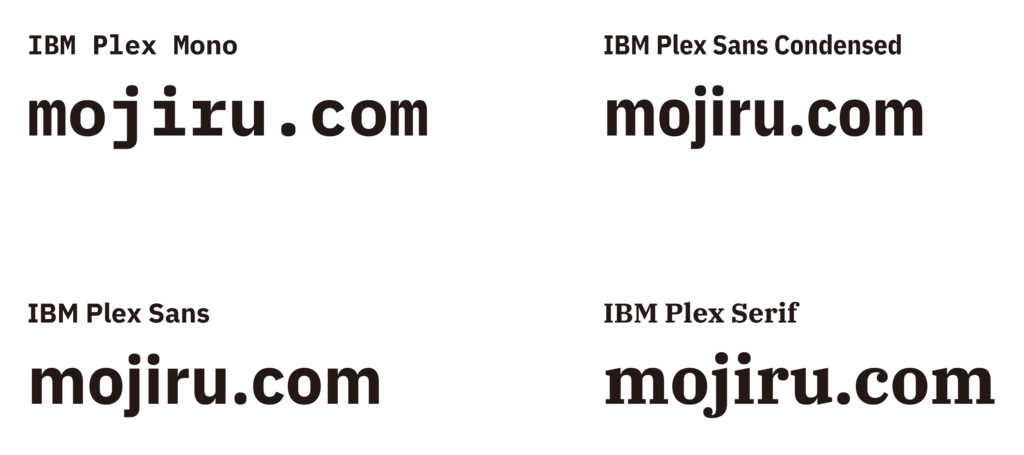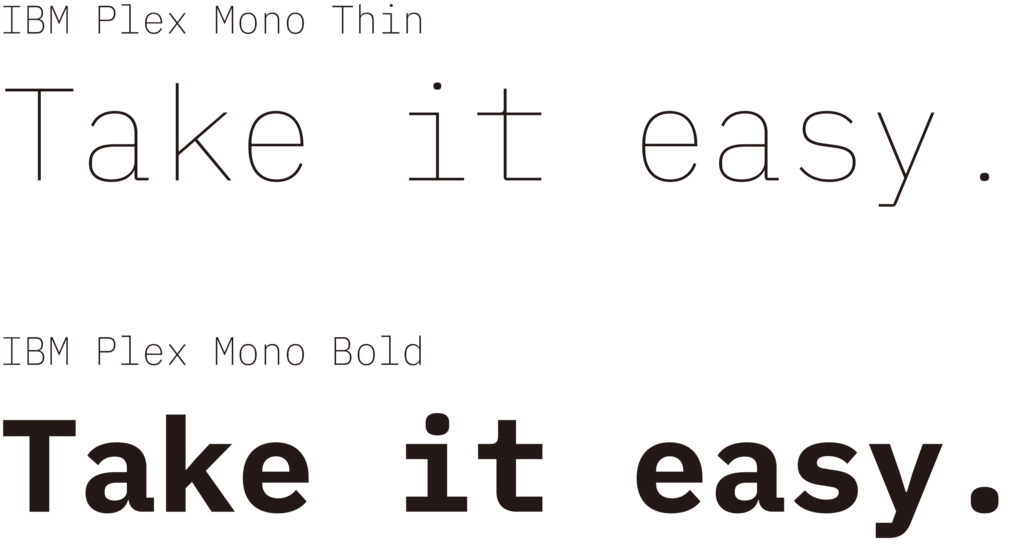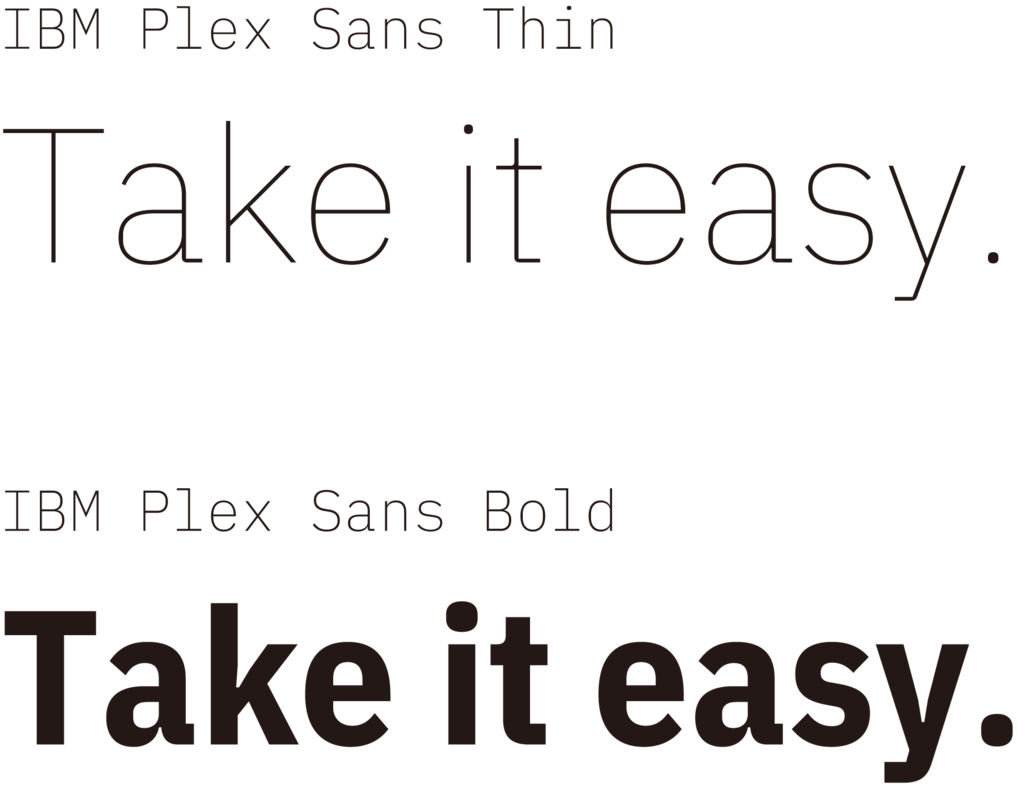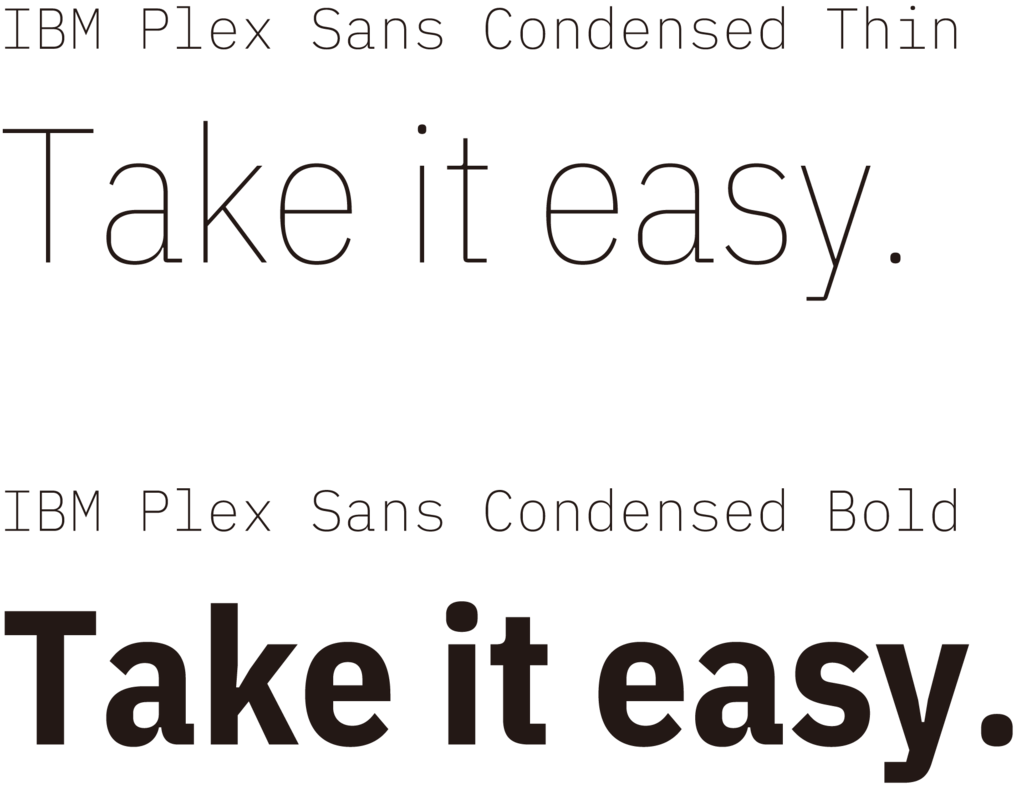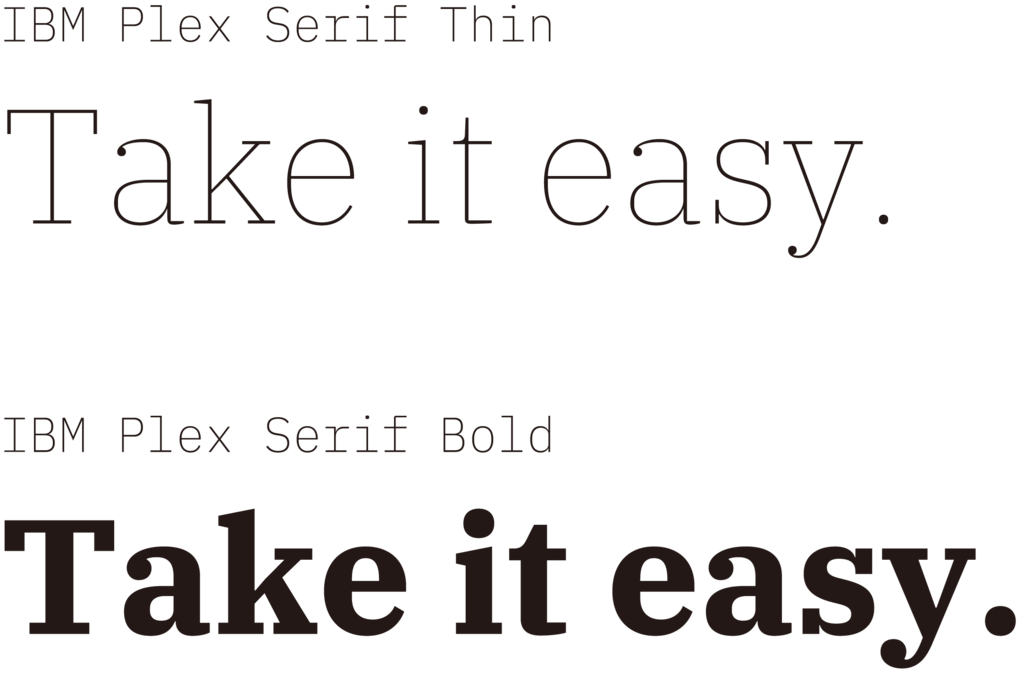
オープンソースフォント・IBM Plex
コンピュータ関連製品およびサービスを提供するIBMがオリジナルフォントセット「IBM Plex」を開発して無料で使えるオープンソース・フォントとしてGitHubで提供している。
「IBM Plex」は、IBM-Plex-Mono、IBM-Plex-Sans、IBM-Plex-Sans-Condensed、IBM-Plex-Serifの4種類の書体がある。
オープンソースフォント・IBM Plex 書体見本
上記の4書体はそれぞれBold。
IBM-Plex-Mono
IBM-Plex-Sans
IBM-Plex-Sans-Condensed
IBM-Plex-Serif
それぞれの書体にはExtraLight、Thin、Regular、Medium、SemiBold、Bold、Condensedのウェイト(太さ)があり、またイタリック体も完備している。フォント形式はTrueTypeとOpenTypeの他、WOFFやEOTなどのWebフォントも準備。
フォントのミステリー:何故、オリジナルフォント「IBM Plex」が開発されたのか?
2018年で創業107年となるIBMでは、コーポレートフォントとして50年以上に渡り、超メジャーフォントである「Helvetica」を使用してきた。そのフォントライセンスには毎年100万ドル(約1億1000万円)以上のコストがかかってきたようだ。そのコストを削減するため、IBM Brand&Experienxeチームは、Helveticaに代わり、IBMのブランド精神と歴史を捉え、印刷物・ウェブ・モバイルインターフェースでも読みやすく、国際的に通用する書体を目指して、IBM Plexを開発した。
「IBM Plex」の今後…、日本語版「IBM Plex」は?
IBM Plexは現在、英語、フランス語、ロシア語など、ラテン文字とキリル文字を用いる96言語に対応。2018年中にアラビア文字・デーヴァナーガリー・ギリシャ文字・ヘブライ文字・タイ文字に対応予定。そして朗報として日本語や中国語や韓国語フォントも2019年~2020年に対応予定とのことだ。日本語版「IBM Plex」のリリースを楽しみに待ちたい。